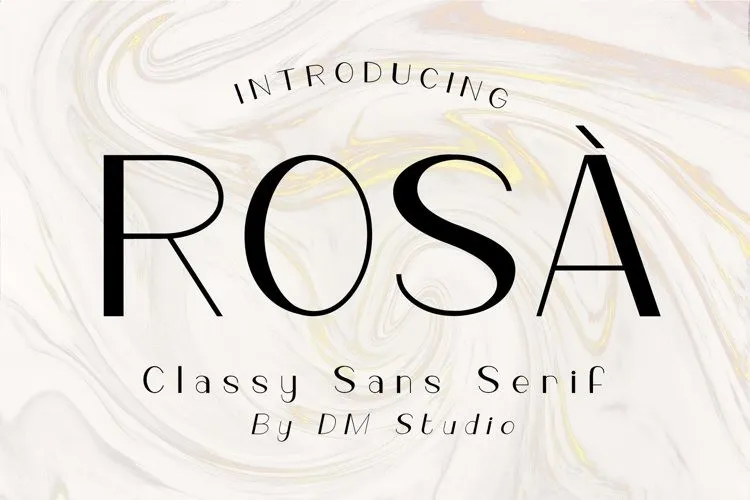
A Rosà Sans Serif é uma escolha perfeita para quem busca modernidade e sofisticação no design tipográfico. Criada por dmletter31 através do site 99designs, esta fonte sans-serif apresenta letras cuidadosamente concebidas para criar textos únicos e memoráveis. Com linhas limpas e um design bem pensado, ela se destaca em diversos ambientes gráficos, desde logos modernos e estilos de marca até headlines de sites ou templates de publicidade. Seu design elegante encaixa-se perfeitamente em qualquer projeto que você esteja desenvolvendo, seja com versões regular ou itálica, sempre garantindo uma aparência atraente e sem esforço. Sem necessidade especial de software para uso, a Rosà Sans Serif é uma excelente opção para designers atentos aos detalhes. Explore agora as possibilidades criativas desta fonte elegante e moderna.